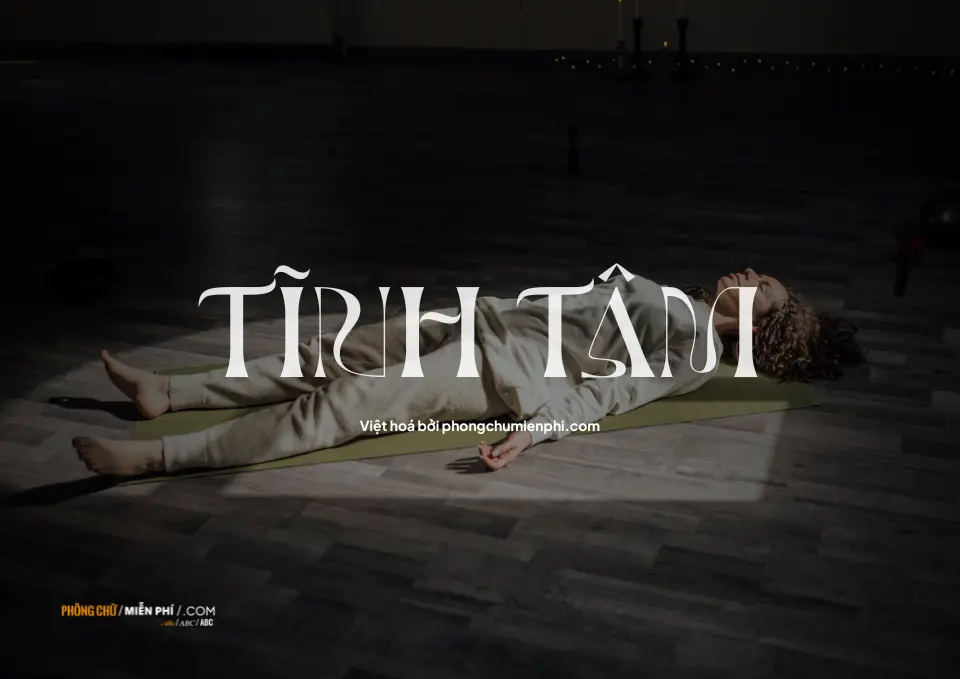
Font chữ Việt hoá PCMP BROWN VOLKY
PCMP BROWN VOLKY, được tạo ra bởi Storytype,
Một phông chữ serif hiện đại và cổ điển với phong cách độc đáo và vẻ ngoài hiện đại.
Phông chữ này hoàn hảo cho logo sang trọng và thanh lịch, thiết kế tiêu đề sách hoặc phim, thương hiệu thời trang,
tạp chí, quần áo, chữ viết, trích dẫn, và nhiều hơn nữa.
Glyph tiêu chuẩn
Chữ thay thế và chữ ghép